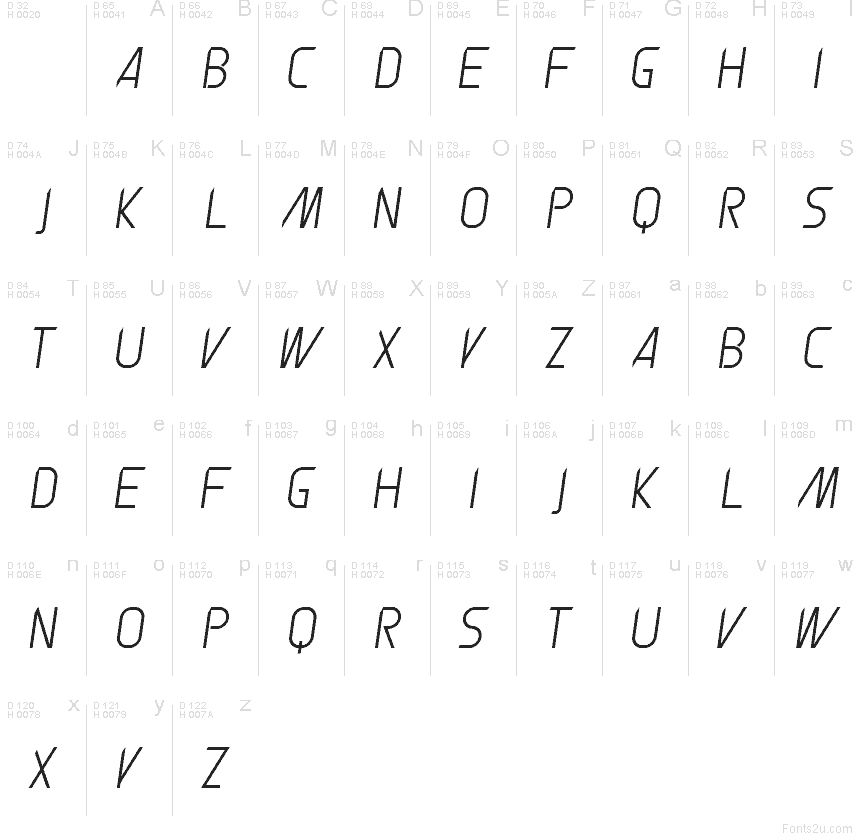
Translator Extravagant Italic od Vladimira Nikoliće je bezplatné techno display písmo s ostrými, dopredu naklonenými veľkými písmenami a elegantným, futuristickým charakterom. Znaky kombinujú široké, aerodynamické ťahy s náhlymi, ako nôž ostrými spojmi a presnými uhlami. Vďaka tomu má písmo rýchly, technický rytmus, ktorý pôsobí skôr ako sci-fi grafika než ako bežná kurzíva.
Prirodzene zapadne do plagátov, brandingu hier, hudobných vizuálov, letákov a titulkov, kde krátke slová potrebujú pohyb a dravosť. Ako bezplatný font sa hodí aj na nadpisy, logá a monogramy, pretože veľké písmená si zachovávajú silnú šikmú siluetu, aj keď je text krátky.